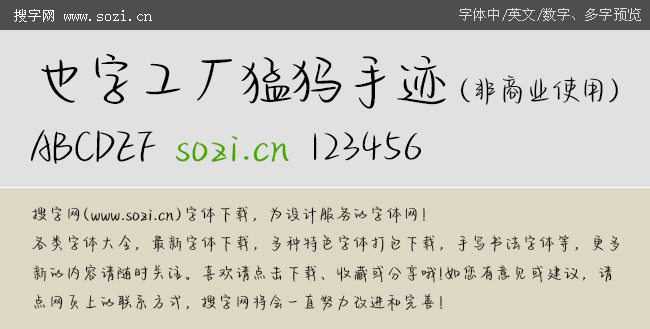
也字工廠猛犸手跡
搜字網(wǎng)給大家提供一款也字工廠猛犸手跡(非商業(yè)使用)中文字體下載,也字工廠猛犸手跡是一款手寫(xiě)書(shū)法字體,字體書(shū)寫(xiě)流暢,自然大方,具有很好的視覺(jué)效果。適合應(yīng)用于書(shū)籍畫(huà)冊(cè)、海報(bào)、網(wǎng)頁(yè)設(shè)計(jì)等應(yīng)用(此字體為個(gè)人非商用版,商用可以聯(lián)系:官方網(wǎng)址:https://yefont.com/home,聯(lián)系方式:13798980448)。